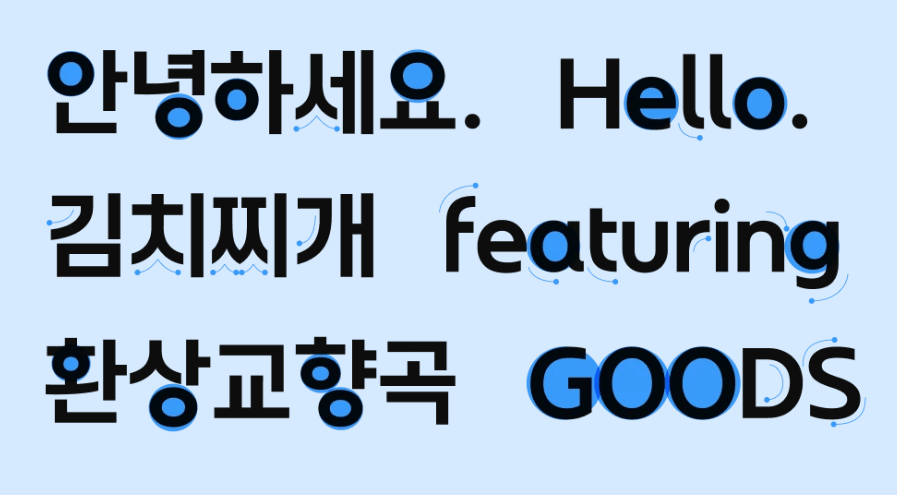
Stunning Sans는 모든 브랜드와 크리에이터가 무료로 사용할 수 있는 현대적이고 세련된 산세리프 폰트입니다. 이 폰트는 다양한 디자인 프로젝트에 적합하며, 특히 정보 전달이 중요한 문서나 웹사이트에서 그 가치를 발휘합니다. 지금 바로 다운로드하세요.
특징
다양한 사용 범위: 웹사이트, 광고 배너, 이메일, 패키지, 비디오 자막 등에 사용 가능합니다.
명확성과 가독성: 명확하고 읽기 쉬운 특성을 가지고 있어, 정보를 쉽게 전달할 수 있습니다.
◑ 산세리프 폰트(Sans-serif font)는 글자에 세리프(serif)가 없는 글꼴을 의미합니다. 세리프는 글자의 끝부분에 있는 작은 장식이나 돌출부를 말하는데, 산세리프 폰트는 이러한 장식이 없기 때문에 보다 깔끔하고 현대적인 느낌을 줍니다.